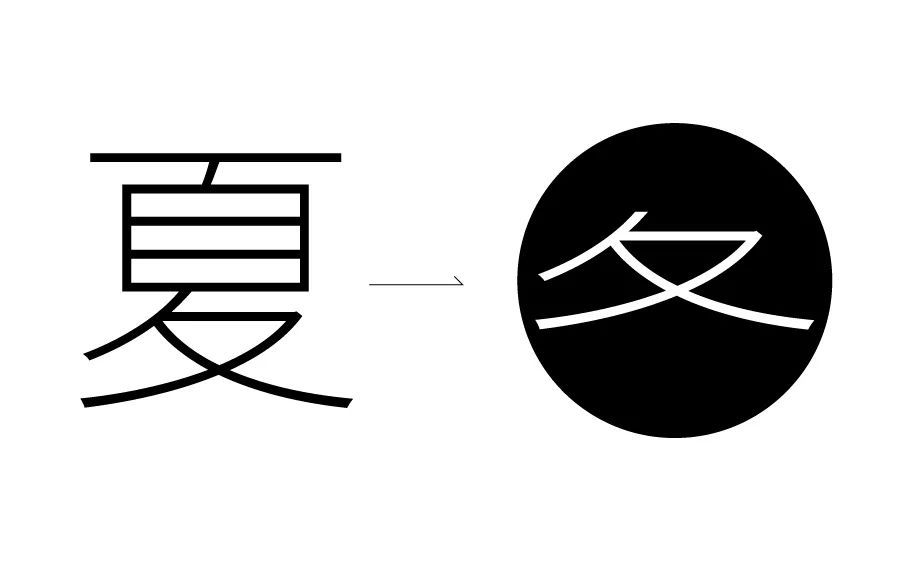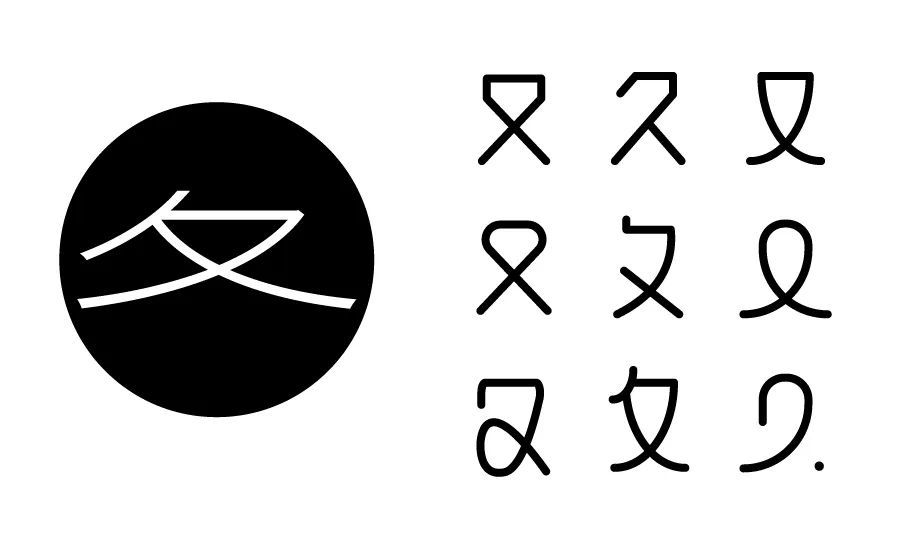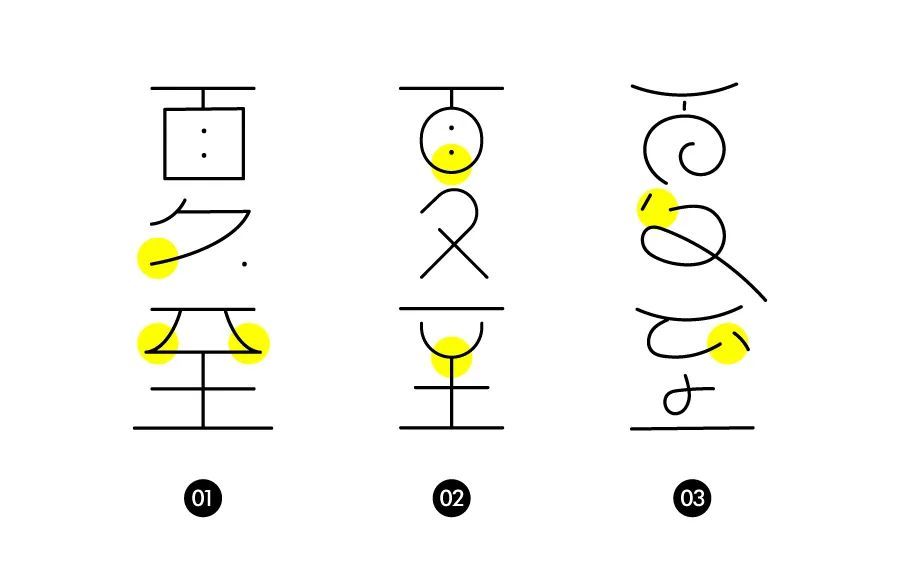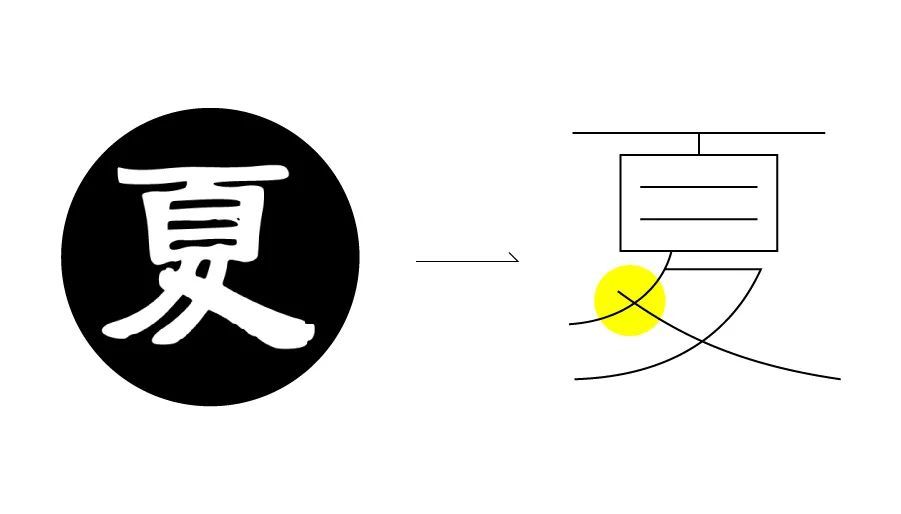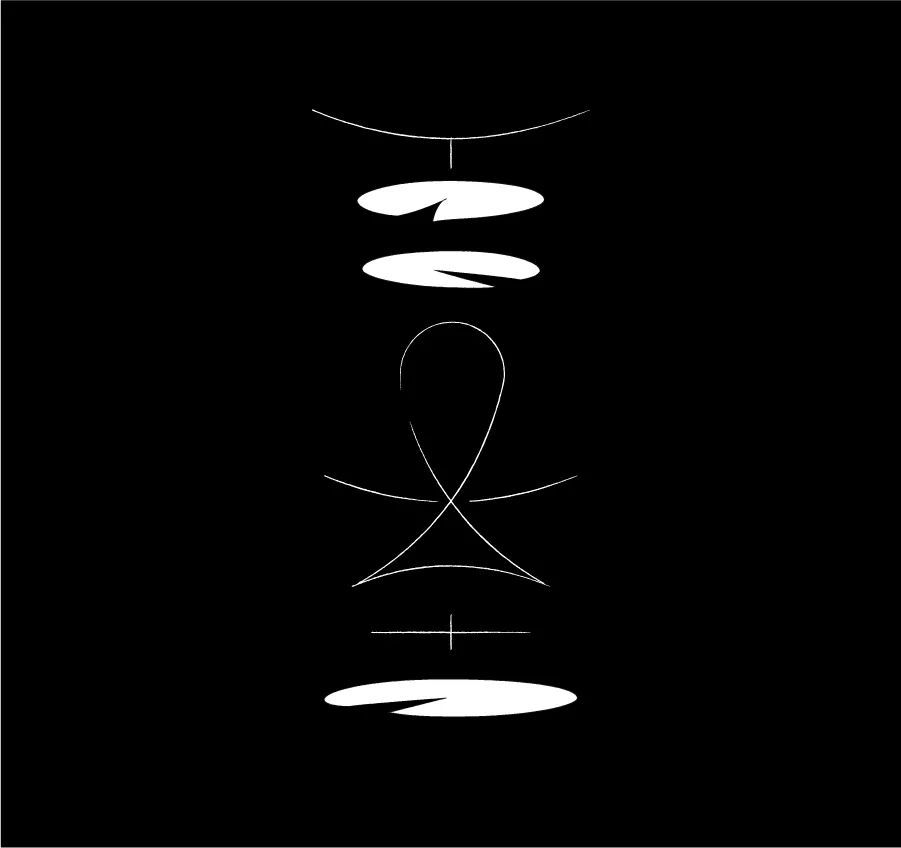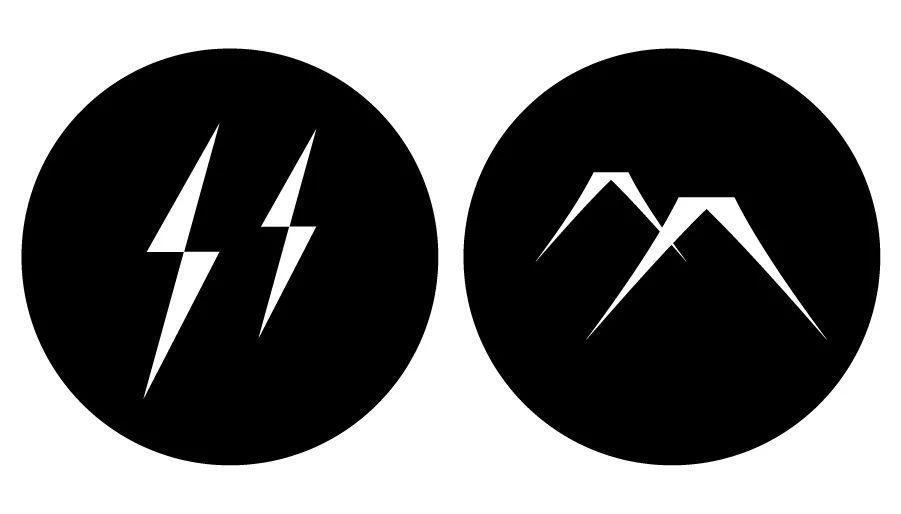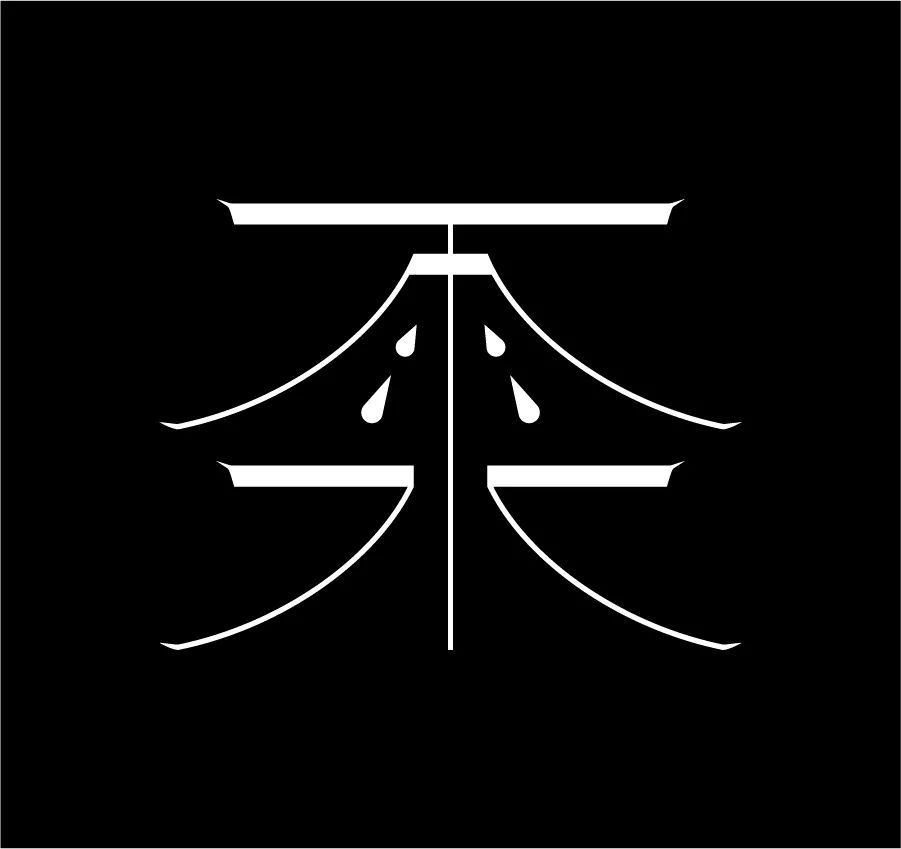
节气创意字体设计
于是我将这个重大任务交给了刺猬老师和刘乾老师。咱们直接今日主题,今天主要分享一下:如何结合字意、分析字形特征从而通过设定某些规则产出具有系列感的创意字体,并且跟动效进行结合。
由于是系列作品,所以在前期尝试的时候我们需要设定一个主题,并且以一组字作为尝试案例设定好基础的规则及创意发散结合的方式。
经常我们在进行创意字形设计时会运用到上面的三个技巧,从字意、笔形结合思维发散的方式展开。
以24节气中的几个为例,惊蛰:时至惊蛰,春雷乍动,假设我们以字意出发,那么春雷乍动,雷光闪电是可以作为思路来源之一。而夏至:我们从笔形出发,是否能够把鱼戏莲叶间的场景与笔画笔形相结合。同样,大寒或者其他的节气都可以此为思路发散展开。
在今天的几组案例实操字形中,我们设定的规则有三个,一是由字意出发或者发散结合得到灵感;二是由基础点、线、面三者进行结合,具有一定的变化节奏;三是秩序,尽可能让整体字形以对称或者对齐化的方式呈现。(这个规则通常是由第一个字形确认得到,这边为了教程便于理解,所以提前说明)
明白了系列字体设计的常用技巧后,我们直接开始案例实操。第一组字形,是确立规则风格的,所以尝试的过程会相对复杂。我们以“夏至”作为主题,通常来说第一组字我会随意进行草稿的尝试。
草稿勾勒,分享一个软件小技巧。选择画笔工具,双击画笔工具后可以将保真度调整到平滑,运用画笔直接草稿。当然你也可以在纸张上用笔进行草图。
从笔形入手,也就是从字体的结构、笔画本身尝试开始设计。而局部整体则是如果将局部笔画的特征延续到整组字,是非常重要的。一般而言,一组字中设定的规则越少,那么特征越强烈,并且统一度越高,越容易把控。我们举个例子来理解。
入手的第一个字,有按顺序来也有按复杂程度来,这个看个人偏好。这边我们按顺序从夏字入手,整个字中相对比较难处理的部分也就是夏字的下半部分。我们可以基于这个部分尝试草稿,也可以寻找一些参考。
可以看到,其实很多的变化都是通过细微调整得到的,比如加圆角、断笔、连笔、点结合等等。
基于某个笔画的特征,我们将特征延续到整组字从而得到不同的草稿方案。如案一,将夏的下半部分曲线提炼结合到至的上半部分。同样的案二则是把椭圆结合。案三则是把手写的感觉结合。其实这三个草稿方案都是基于某个笔画特征,将局部与整体结合得到方案。
前面是比较自由的草稿,现在我们可以尝试从古籍字形中去寻找一些灵感,或者从字意发散后得到一些图形结合的方法。
从古字中我们能够得到许多的灵感,比如连笔的处理方式,笔画笔形的灵感,不同的楷书、行书、隶书结构上的不同,或者笔画的处理方式等等。
例如上面的草稿尝试,我们可以通过借鉴隶书中对夏字下半部分的处理方式,从而让整个字形结构更为稳定。
从字意角度出发,夏至联想到鱼戏莲叶间的场景,尝试寻找一些相关的元素表达方式,如水墨画,线性画等等。
我们将莲叶造型提炼概括,便于与字形结合。由于莲叶造型扁平容易与笔画结合,但是鱼的造型过于具象,结合难度较大,暂时搁置。我们先尝试用莲叶结合字形。
在尝试搭建夏字时,无意中尝试出夏字下半部分可处理为类似鱼的造型,为了契合鱼戏莲叶间的含义,考虑尝试将至字结合。
通过将至字与夏字上下结合,最终得到莲叶在上下,而鱼造型通过两字笔画结合得到体现。这样第一组字基本确定,风格和规则也基本确定。
有了第一组字定下风格和规则,后续的系列字形相对而言难度会小一些,我们可以不必做太多的风格尝试,而把精力集中于如何延伸。我们来做一组惊蛰,这组字形也是难度较大的。
依旧从字意出发,先构思相关元素,时至惊蛰,春雷乍动。相关的元素如闪电,虫草等都可。
从构思的元素方向中提炼出造型,很明显的能发现这两组造型元素与字体结合的难度会偏大,其实在实际操作过程中我们可以尝试非常多不一样的造型方向,只要契合主题便可,这边仅做简单演示。
因为案一中设定的规则之一是线和面的对比结合,所以我们基于规则,先用线尝试搭建出基础字形。那么搭建的时候可以加入一些自己的想法,比如几何造型结合等设计手法。同时观察是否有可以结合图形元素的位置,这边能够发现,角度统一的地方可以尝试加入春雷闪电元素。
将春雷闪电的元素与线构成的基础字形结合,基本上惊蛰的方案已经出来了。实际上在设计的过程中结合的位置,以及角度等都是需要不断尝试的,这边不再赘述。
前面两个方案的思路都是比较相似的,我们再来做一个有些许区别的,以及在细节的刻画上差异较大的案例。大寒。
我们可以直接从具象的景物,照片等提炼一些灵感来源。比如这是我搜大寒得到的一些相关景象。
大雪堆积的场景,屋顶飞檐翘角可以提炼为笔画的末端。
我们先用线搭建出整个的字形的骨架,再来将前面设定好的笔形笔画融合进来。
可以看到这边细线笔画部分是有细节刻画处理的,结合了飞檐翘角的特点。而为了做出线和面的对比形式感,所以把撇捺以及点加粗,让其有线和面的对比,从而跟前面的字形产生系列感。
我们再来做最后一个案例给刘乾老师的动效部分做一个铺垫,这个我们做一个相对简单一些的,沿用一下大寒的思路。
雨水的元素相对而言会好提炼很多,水滴、雨滴是很容易联想到的元素,并且有大寒的基础,我们也很容易将笔画的处理方式与飞檐翘角相结合。
雨滴的处理方式以曲线结合,飞檐则相对锐利一些,刚柔对比。
同样先搭建出基础结构,在搭建基础结构的时候我一般都是直接用画笔草稿,或者在纸张上画手稿。如果说基础较差的同学是可以先按前面的尝试方法去寻找一些参考来辅助搭建结构。
最后我们将设定的笔画与特征跟基础结构相结合,方案也就基本完成了。接下来我们让刘乾老师给大家演示一下动效部分。
接下来咱们开始雨水二字“动作片”的部分。在让它们动起来之前,我们可以假象自己是导演,在脑海里对整体动态的逻辑有一个大体构思。
首先我们分析文字本身以怎样的方式运动,我这里通过让每组笔画依次出现的方式,来做出丰富的层次感。通过拆解,将二字转换为以上基础图形,便于思考。
最基础的横竖笔画,可以用AE的缩放属性,单独缩放X轴或者Y轴,做出擦写出现的动态。
这里要注意一点,例如我们要让笔画左右同时做动作出现,就要用向后平移锚点工具把中心点放置在图形的中间位置。
同理,若是想要笔画从左边出现,就要把中心点定位在右边的末端,如要从右边出现,则要做相反的运动。竖笔定位在上端,对Y轴做缩放。
撇捺笔画无法通过缩放来实现擦写出现的动态。需要在笔画上方绘制弧度相似的路径,然后叠加在上方,做修剪路径的动态。然后在轨道遮罩里面选择Alpha遮罩即可。
类似于雨滴的点的笔画通过位置属性做运动,从上方落下即可。
文字本身的动态做完后,为了突出雨水二字的含义,再做一滴雨从笔画的竖笔落在地面溅起水花的状态。方法同样利用基础的位置属性,然后调节移动的运动轨迹。
完成整体的动画后再添加一个简单阻塞工具,将阻塞遮罩调节的大一点,就会出现如图所示的笔画粘连的细节。